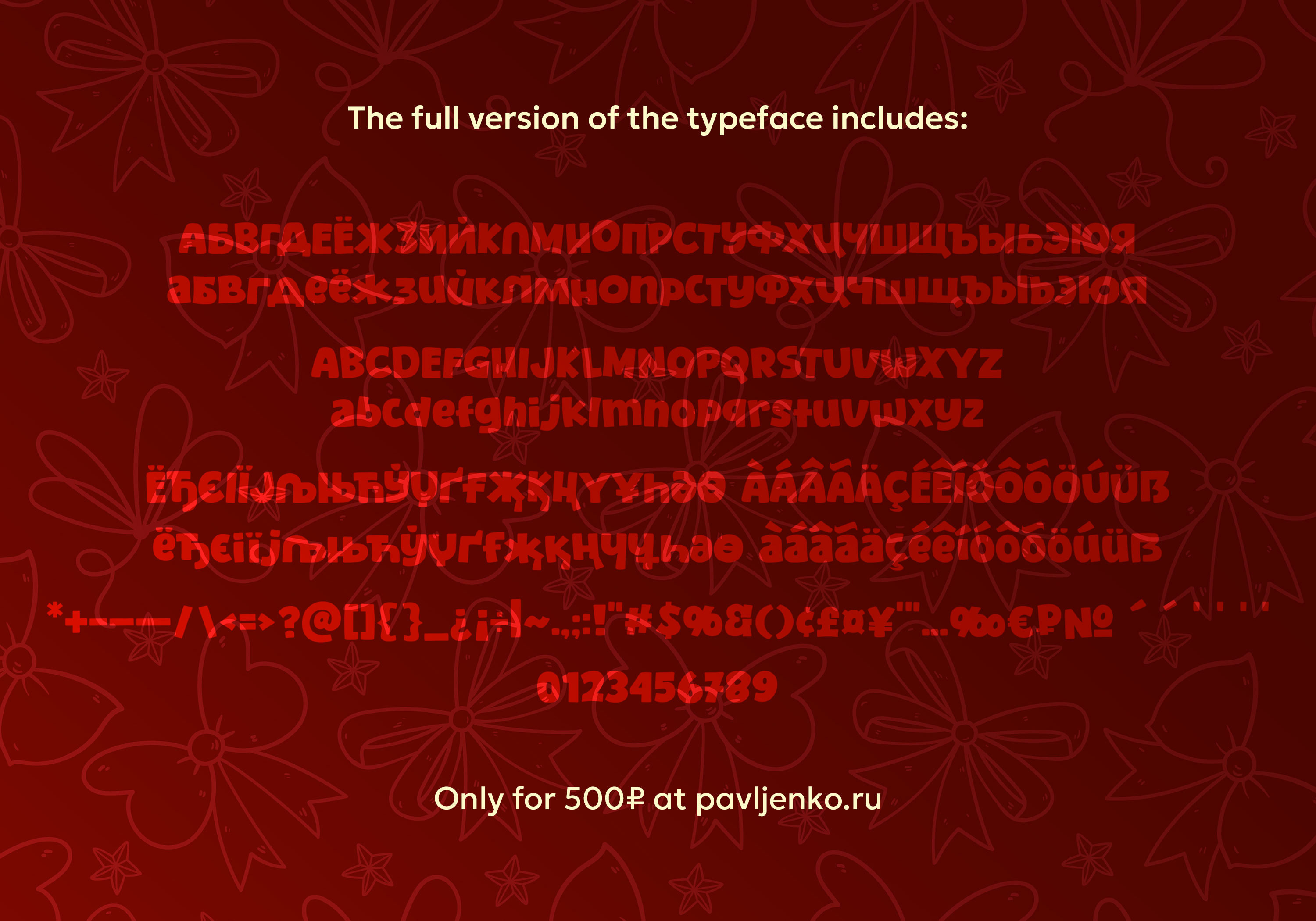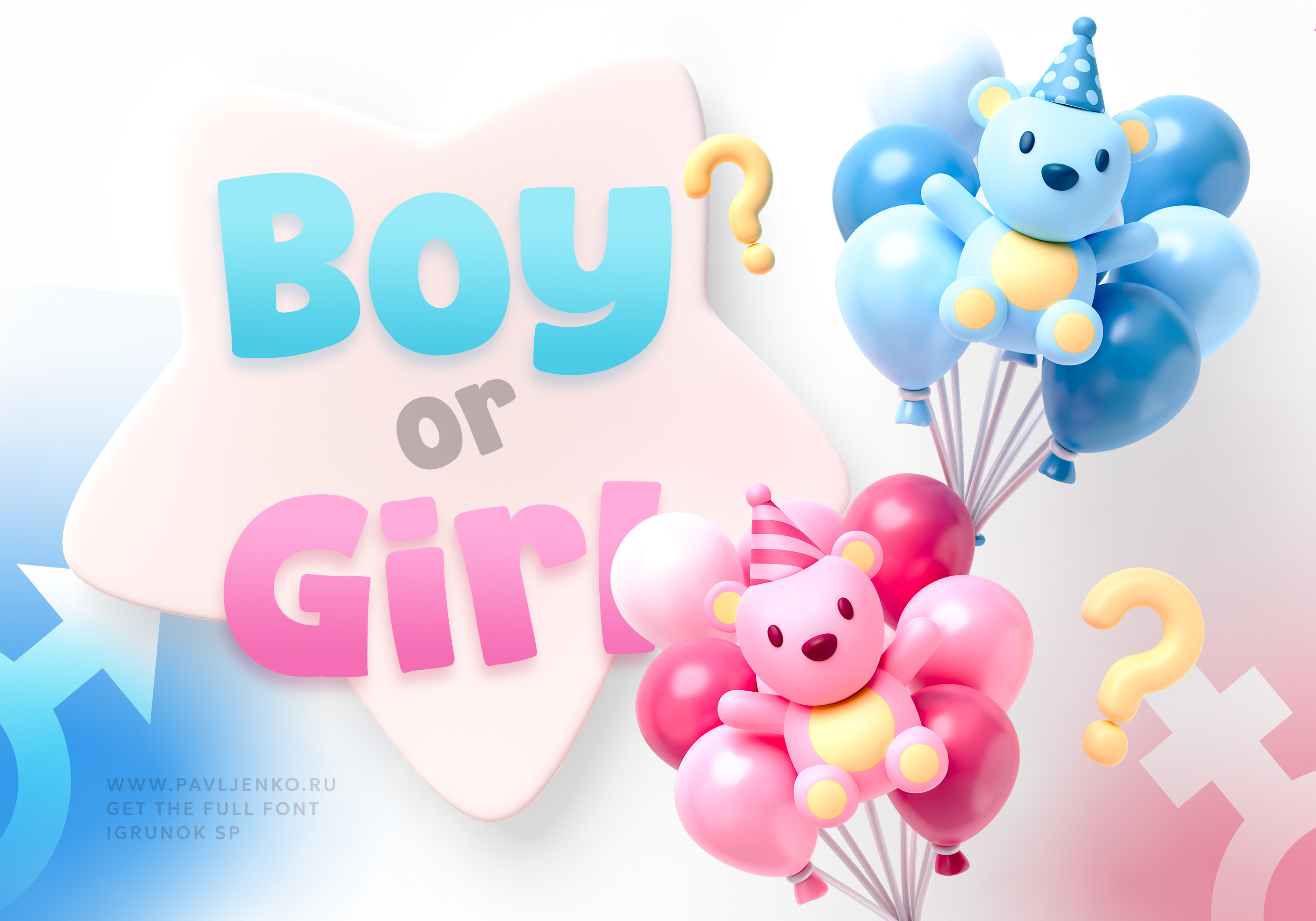
Шрифт Игрунок
Igrunok — мягкая пластика и округлые, чуть надувшиеся формы. Плавные штрихи, сглаженные окончания и нерегулярный ритм создают ощущение движения и доброжелательности. С ним оформляют крупные заголовки и логотипы, коробки сладостей и детские товары, афиши ярмарок и утренников. Строгость здесь ни к чему: тон задаёт сама форма — лёгкий, почти игровой. В комплекте — полная версия STAR и лицензия.
Designer Sasha Pavljenko